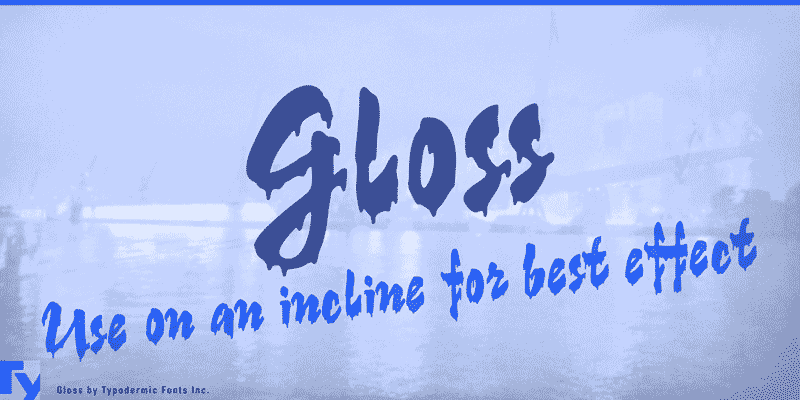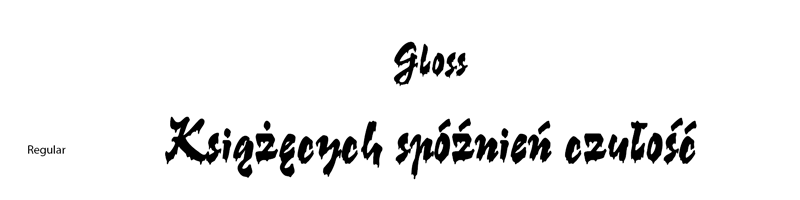
Font Gloss
Do naszego studia trafił font Gloss, zaprojektowany przez Günter Gerharda Lange i Raya Larabie. Litery w tej ozdobnej czcionce mają charakterystyczny efekt ściekającej farby.